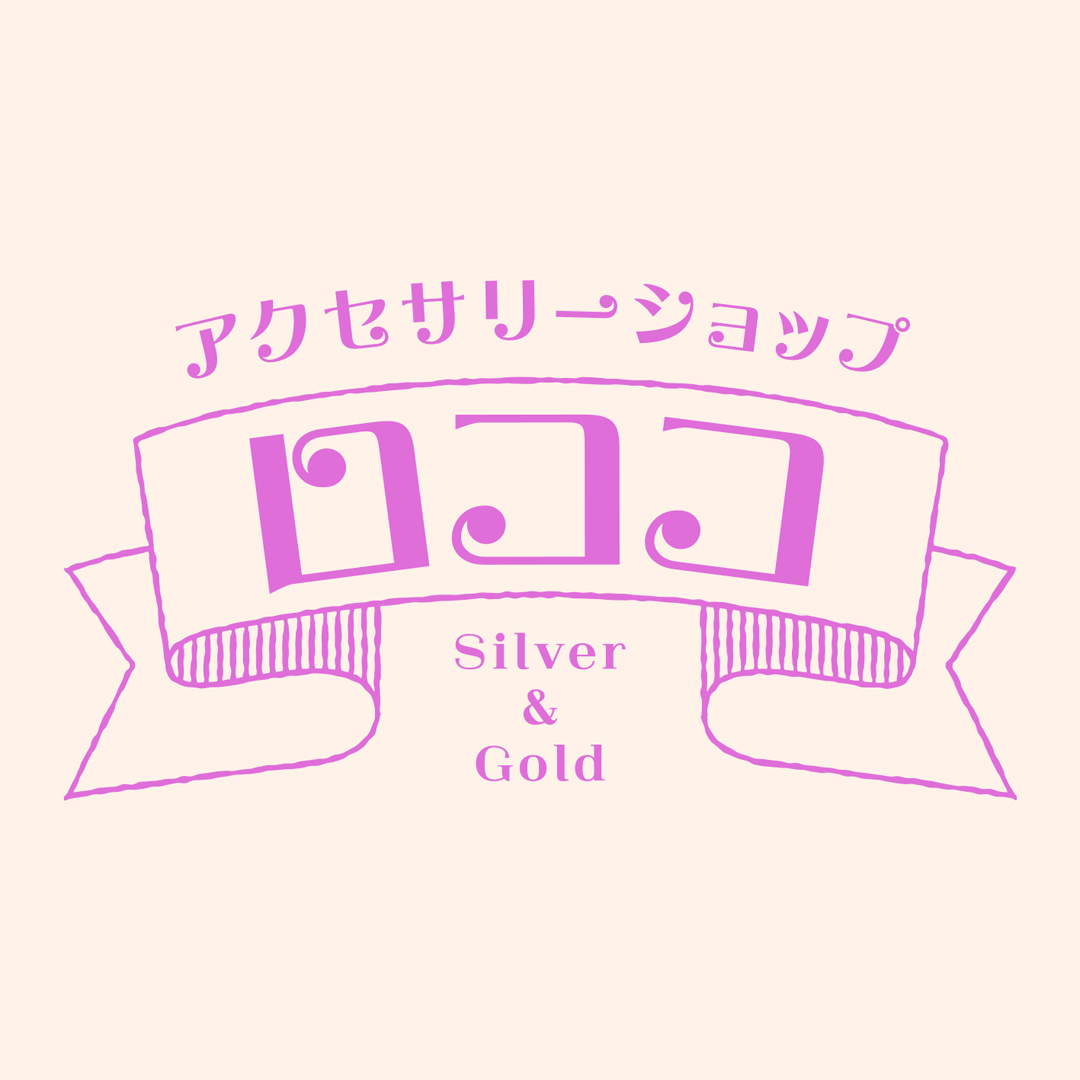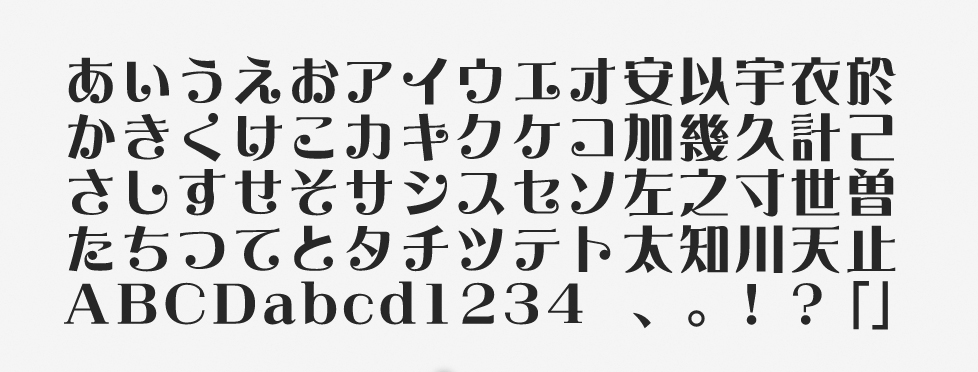
「翠流デコロマン」について
翠流デコロマンは2022年秋の新書体として提供が開始されたフォントです。同時リリースされた翠流ネオロマンのかな文字をベースとしながら、より華やかなイメージに仕上げられました。モリサワ制作のかな文字と英数字に、Arphic TypesのAR浪漫明朝体の漢字が組み合わせられています。
「翠流デコロマン」の特徴
翠流ネオロマンとの違いとして、エレメントの先端や濁点の部分に装飾が加えられています。これが華やかな印象につながっているポイントです。かな文字はきらびやかな印象で、漢字の重心はやや低めに設計されています。
フォント名に「ロマン」という文字が含まれるように、たとえば広告や動画テロップなどでロマンチックな世界観を演出したい場合には特に効果的です。文字自体が確固たる世界観を持った個性的なフォントと言えるでしょう。
翠流デコロマンは、カールしている部分がとても可愛らしいデザインです。昭和レトロ・平成レトロのような雰囲気を出したいときに使いやすいですね。そのほかのシーンでも、あえて使うことで面白い効果を生み出せそうで、可能性が広いフォントです。